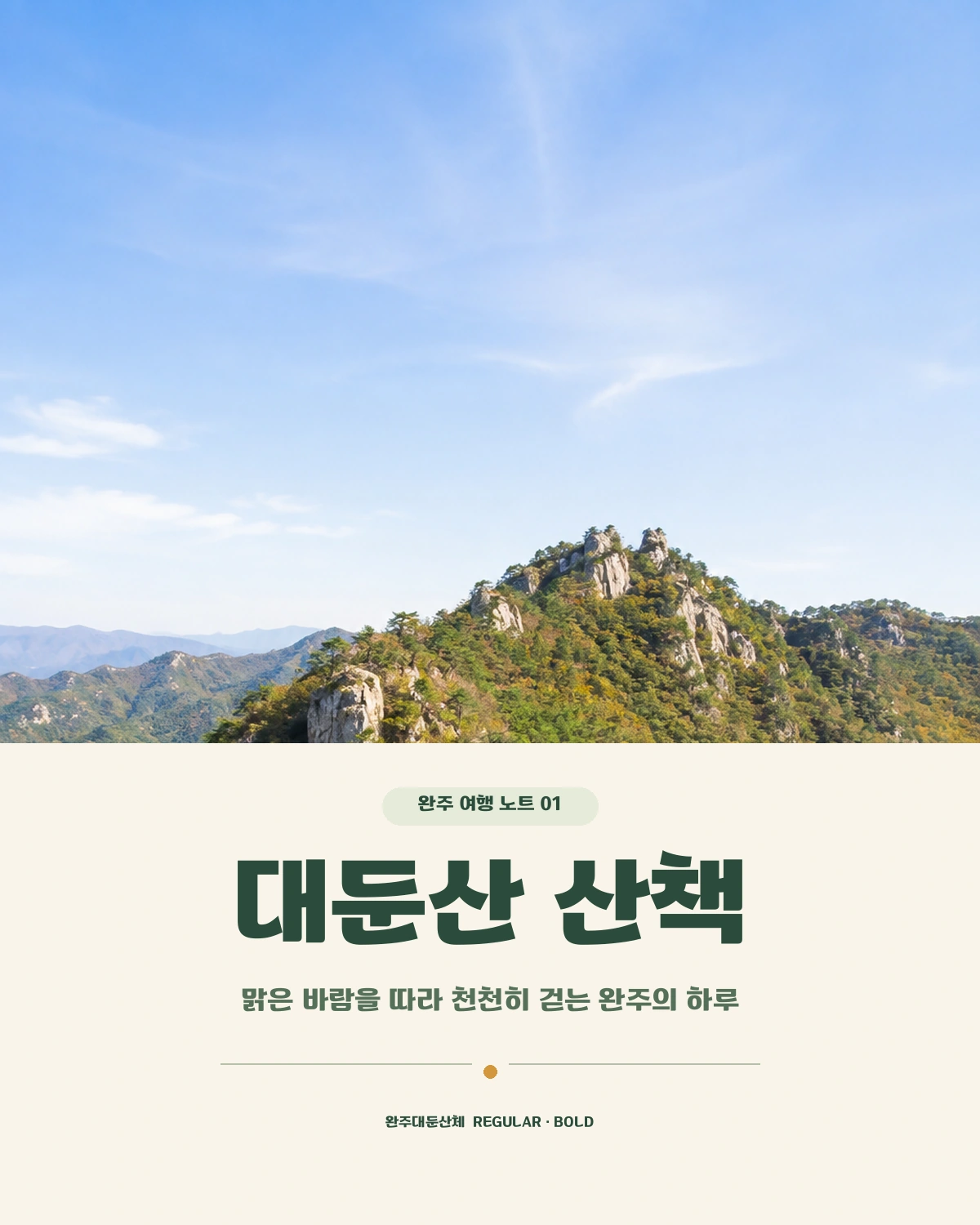
완주대둔산체 — 완주군에서 배포하는 무료 폰트입니다. 대둔산의 절경과 웅장함, 케이블카의 꽉 찬 형태감을 좌우 대칭으로 담아낸 제목용 서체
완주군이 2023년에 무료로 푼 전용서체입니다. 완주누리체와 두 벌이 한 세트로 함께 나왔고, 전북의 군 단위 자치단체로는 유일한 전용서체 개발 사례로 소개됩니다.
모티브가 셋입니다. 완주를 대표하는 명산 대둔산의 절경과 웅장함을 굵게 표현했고, 여기에 대둔산 케이블카의 꽉 찬 형태감과 구름다리의 선을 이미지화한 대칭적인 디자인을 더했다고 밝히고 있습니다. 산 하나에서 능선과 케이블카와 다리를 각각 뽑아낸 셈입니다.
조형 설명도 붙어 있습니다. 직선을 주로 쓰면서 자소마다 곡선을 적용해 부드러움을 표현했고, 세로획과 가로획의 굵기를 고르게 해 제목체의 주목성을 부여했다는 것입니다. 파일에서 재어 보면 낱자가 가로로 퍼져 있고 자면을 넉넉히 채워 인상이 굵고 단단합니다.
굵기는 두 가지이고 현대 한글 11,172자를 모두 담았습니다. 제목용으로 만들어졌으니 긴 본문에는 맞지 않습니다. 라이선스는 공공누리 제1유형이라 상업적으로 쓸 수 있는데, **출처 표시가 의무**입니다. 무료라고 그냥 쓰시면 안 됩니다.